汉字是一种独特的文明。上古先民最早采用的原始记事方式有绳结、木刻、图画以及在器物上划刻痕迹,随着一些符号化的痕迹被反复使用和在使用原始记事方式中所积累的经验孕育了汉字文化。
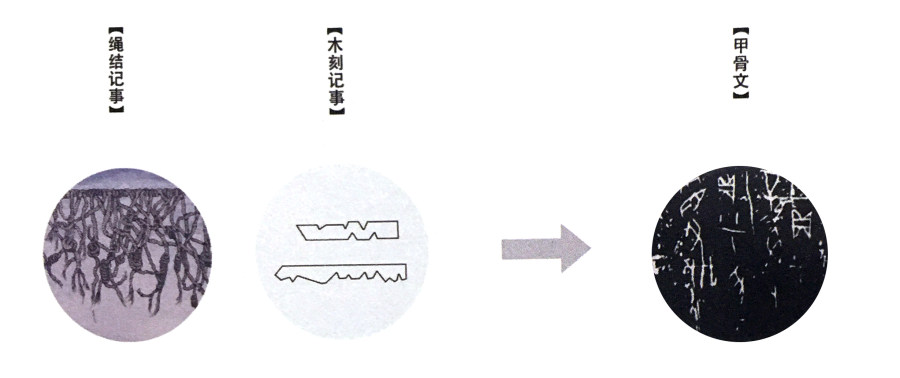
汉字是我国古代先民发明的一种记载性工具,由记事符号和记事图画演变而来,随后发展成为甲骨文。甲骨文是我国已知的、最早的,以记事为主的可识别性文字,是世界上最古老的文字之一,它的发展演化前后经历了3500余年,这在中国5000余年的历史文明中意义重大。中国汉字文化源远流长,它的发展经历了甲骨文、金文、篆体、隶书、草书、楷书、行书等几大过程。
随着汉字的不断发展,我们可以看到汉字无论是从书写方式,还是从字体形态上来说,都在进步。归纳来讲,就是越来越注重简化性、识别性和艺术性。而在手写体字形设计中,也同样需要遵循这样的原则。